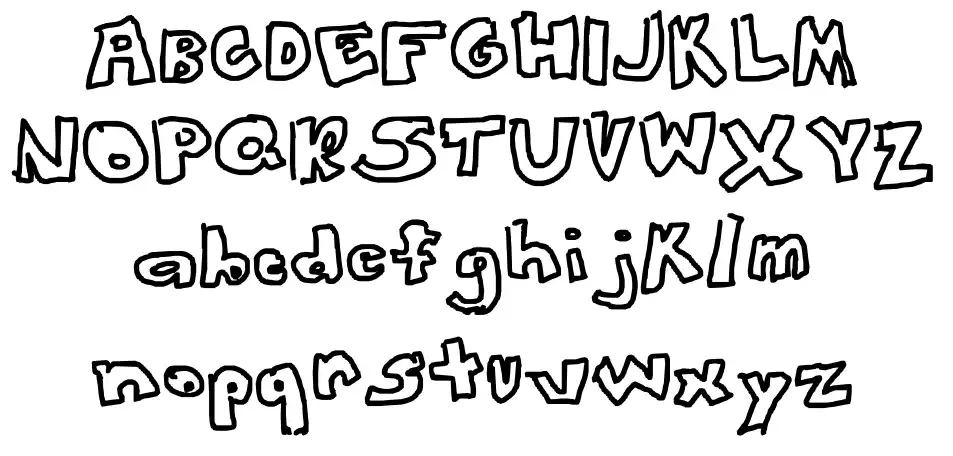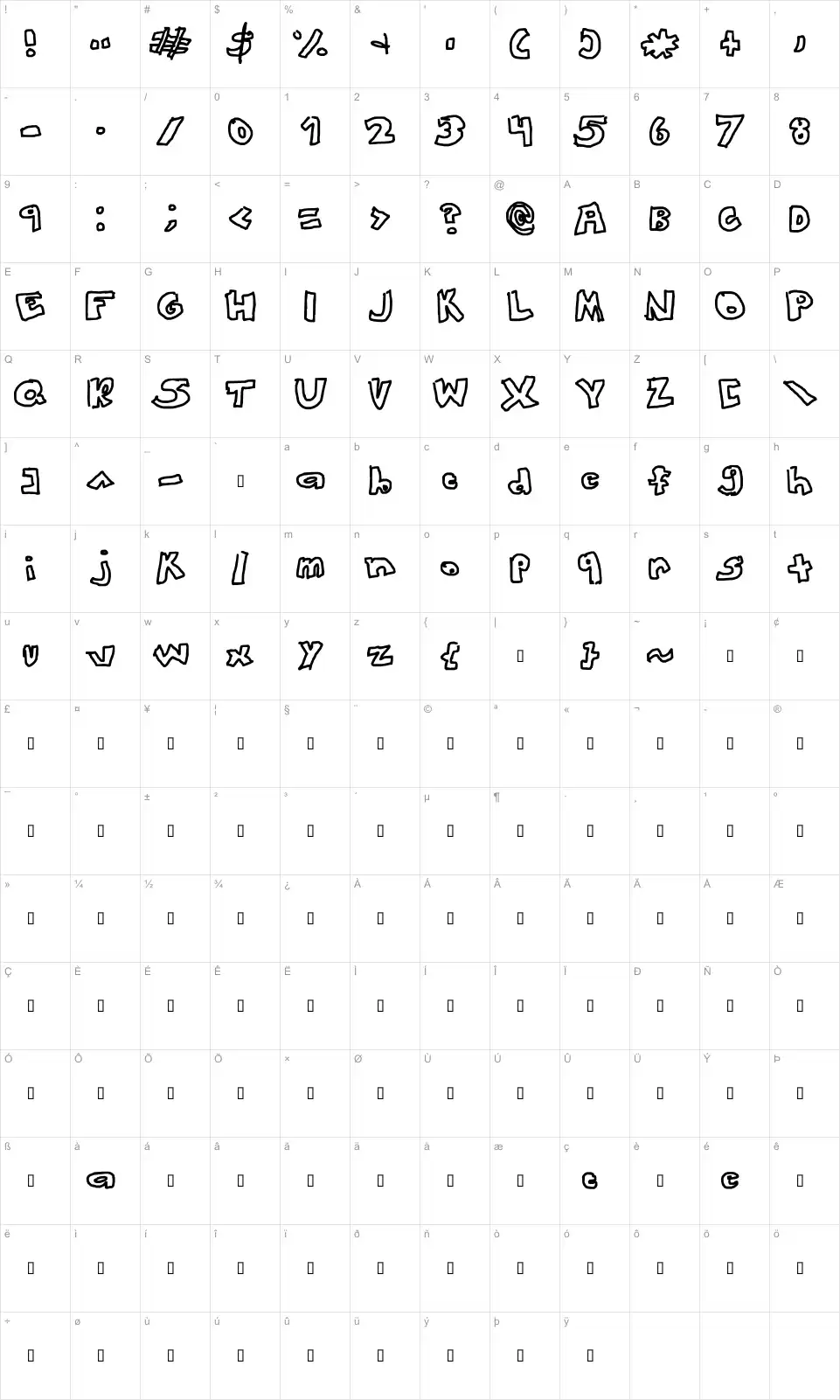
A fonte “This Font Looks Awesome”, criada por Jennifer, oferece uma experiência visual única e divertida. Se você está procurando por esta fonte ou quiser testá-la antes de incorporá-la em seus projetos, você pode facilmente baixá-la ou gerar um pré-visualizado de texto personalizado online para ver como ela se destaca em diferentes estilos e tamanhos. Esta font, que faz parte da categoria Fancy e do gênero Cartoon, foi adicionada em 12 de julho de 2022 e já foi baixada pelo número importante de 1580 usuários. Com um tamanho de 20 KB, esta font é extremamente compacta e adequada para um uso variado em projetos digitais.
Designer: Jennifer